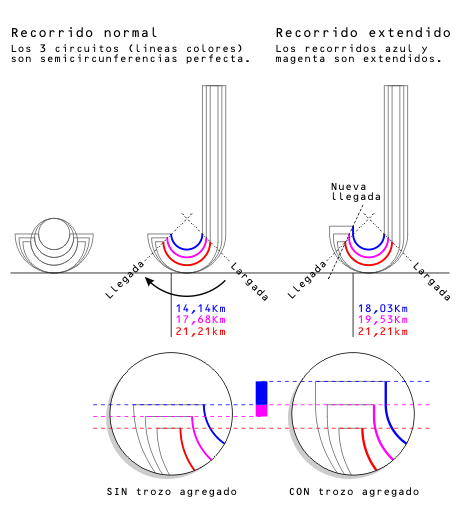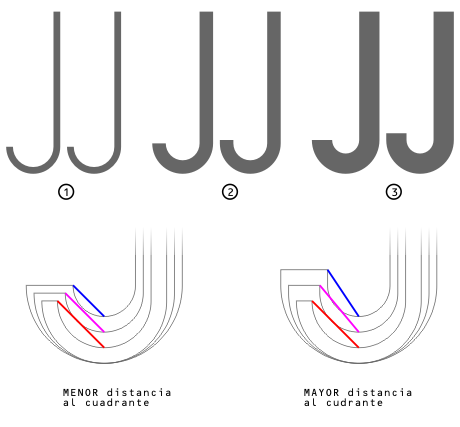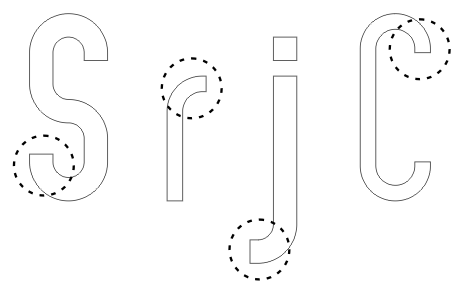
Tipografía Trescirc – Parte 5: analizando la curva
Como parte de la creación de mi tipografía [Creando mi propia tipografía], fueron apareciendo cuestiones que hubo que ir solucionando. Entre aquellas se encuentra el caso de las letras que en la tipografía que estoy haciendo tienen terminaciones curvas, como las que se muestran en imagen:
En los tres pares de letra J que se muestran en la imagen, la letra de la izquierda mantiene la curva igual a la de un semicírculo, mientras que la letra de la derecha de los pares 2 y 3 modifican su terminación curva. ¿Por qué hice esta modificación?
Si medimos las distancia desde el cuadrante inferior hasta el final de la curva (líneas diagonales de colores) se ve que las distancias son cada vez menores en las letras J de la izquierda. En las letras de la derecha se va incrementando.
Este incremento tiene su explicación: imaginemos un circuito de carreras de autos. En nuestro caso sería la curva final de la J, desde el comienzo de la semicircunferencia hasta su final:
En el “recorrido normal”, las distancias en Km de las pistas azul y magenta van siendo cada vez menores, y terminan de manera más brusca respecto a la pista roja.
Para resolver ambas situaciones, o sea:
1) diferencia de distancias en ambas pistas (azul y magenta) respecto a la roja, y
2) terminación abrupta (curva cerrada) en pista azul y magenta,
se añade al final del recorrido un pedazo de pista adicional, modificándose también la línea de llegada en la azul y en la magenta.
Aun agregándole el pedazo extra de recorrido, el circuito rojo sigue siendo el más largo de los tres; sin embargo, la diferencia de distancia entre los 3 recorridos se recompensa de la siguiente manera:
• Al tener la pista azul una curva más cerrada, el vehículo no puede tomar la curva muy rápido, y tiene que ir más despacio para no salirse de la pista, por lo tanto tiene menor largo de pista a causa de no poder alcanzar velocidades altas y poder ganar la carrera.
• La pista roja al poseer una curva más abierta, el auto puede alcanzar mayor velocidad, e ir mas rapido, por lo tanto es más largo el recorrido, para equilibrarlo con la pista azul, la cual es más lenta.
Así entonces los tres  autos tienen la posibilidad de ganar la carrera.
El trozo que se agrega al circuito de las pistas azul y magenta también soluciona el problema #2, permitiendo una llegada más “suave” que si no tuviese ese espacio extra al final del recorrido.